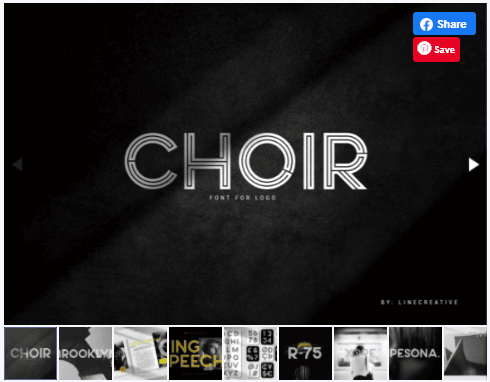
Choir Font
Choir - это современный и крутой дисплейный шрифт. Этот шрифт идеально подходит для написания веб-дизайнов, визиток и всего остального, что требует уникального подхода.